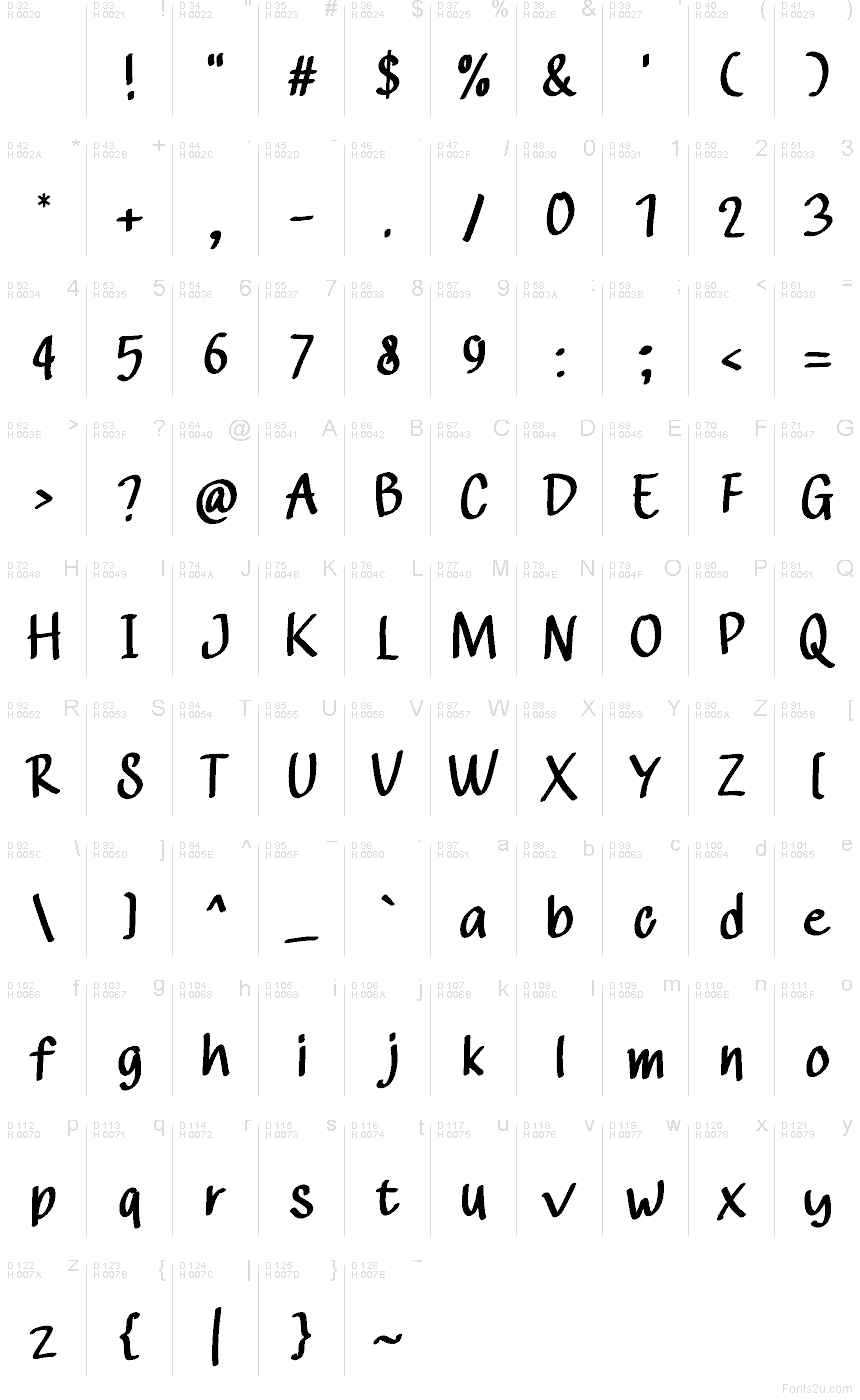
Aflah Type
Aflah Type, créée par Hello Good Studio, est une police manuscrite gratuite au rythme script brossé décontracté. Avec ses tracés arrondis et ses formes légèrement inclinées, elle confère à chaque mot une touche authentique. Les lettres s'enchaînent avec une fluidité naturelle, tout en conservant le charme d'un dessin à la main au niveau des terminaisons et des ligatures, sans paraître trop lisse.
Aflah Type est idéale pour vos citations graphiques, logos, publications sur les réseaux sociaux, cartes de vœux et packagings nécessitant un rendu manuscrit. Cette police gratuite convient également parfaitement aux titres d'invitations et aux étiquettes produits, apportant une dimension humaine sans jamais paraître désordonnée.